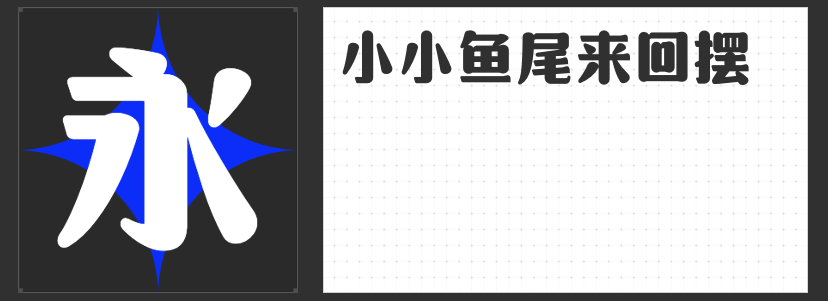
圆润美学新范式:四款设计感圆体字体深度推荐
在平面设计的视觉语言中,圆体字体以其独特的亲和力与现代感,成为品牌传达温度、营造氛围的重要载体。本文精选四款风格各异的圆体字体,从结构特征到美学价值进行专业解析,为设计师提供多元化的选择参考。
一、励字圆梦简 中黑
这款字体以直线笔画为骨架,通过竖折结构替代传统弧线,在保持简洁性的同时融入圆弧转角设计。其外圆内方的结构特征,既延续了黑体字形的稳定感,又通过中宫松散的布局赋予文字呼吸感。笔画起收处的微弧处理,如同书法中的"藏锋"技法,在理性几何中注入人文温度。适用于需要平衡专业感与亲和力的品牌标识设计,尤其适合科技、教育领域的视觉系统构建。
二、字圈也字多肉体
突破传统圆体字形的范式,这款字体将所有转折处转化为封闭圆环,形成独特的视觉韵律。笔画间的负空间被巧妙利用,每个字符都成为充满生命力的视觉单元。其Q弹可爱的质感源于对笔画粗细的精准控制——主笔画饱满圆润,装饰性笔画则以纤细弧线收束,形成视觉层次的对比。这种充满童趣的设计语言,特别适合文创产品包装或年轻化品牌视觉系统。
三、励字粗圆简繁
通过加大字面比例与笔画粗度,这款字体构建出强烈的视觉存在感。方正的结构中融入圆角处理,既保持了黑体字形的端正感,又通过柔和的笔形消解了粗体字的压迫感。繁简同体的设计特性,使其在跨文化传播中具有独特优势。适用于需要强化品牌记忆点的标题设计,或作为正文字体的辅助型强调字体使用。
四、励字星宜简
这款字体的设计语言充满实验性——将厚重笔画拆解为几何模块,通过圆形转角进行拼接重组。起落笔处的圆形装饰与笔画中的断续处理,营造出类似儿童涂鸦的天真质感。这种"不完美"的美学表达,恰恰契合后现代设计对真实性的追求。特别适合卡通形象设计、儿童读物排版或需要营造轻松氛围的创意海报。
这四款字体通过不同的结构创新与美学表达,共同拓展了圆体字的设计边界。设计师可根据品牌调性选择。每款字体都承载着独特的设计哲学,等待设计师在具体项目中激发其最大价值。